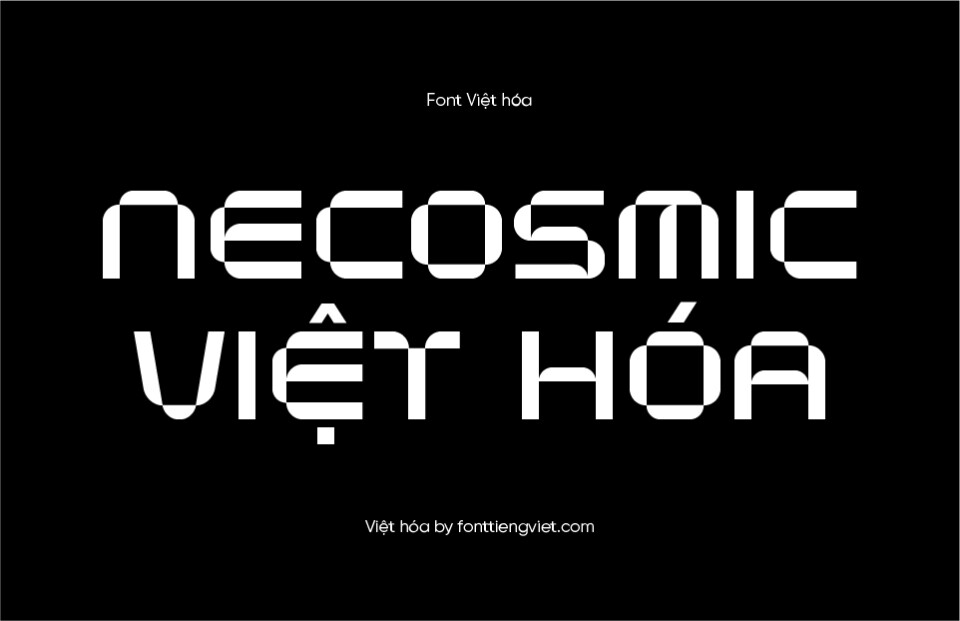
Font Việt hóa 1FTV Necosmic
Tải Font Việt hóa 1FTV Necosmic – Nét Chữ Hiện Đại Cho Thiết Kế Sáng Tạo
Giới thiệu về Font Việt hóa 1FTV Necosmic
Trong thế giới đồ họa hiện nay, việc lựa chọn một Font Miễn Phí chất lượng đóng vai trò then chốt giúp sản phẩm trở nên thu hút. Font Việt hóa 1FTV Necosmic là một trong những bộ font mang phong cách hiện đại, được thiết kế với các đường nét mạnh mẽ nhưng không kém phần thanh thoát. Bộ font này không chỉ giúp các bạn học sinh dễ dàng làm bài thuyết trình mà còn hỗ trợ đắc lực cho giáo viên trong việc soạn thảo giáo án điện tử sinh động hơn. Necosmic mang đến một hơi thở mới lạ, giúp các văn bản tiếng Việt thoát khỏi sự đơn điệu thường thấy.
Ưu điểm nổi bật của Font Việt hóa 1FTV Necosmic
Thiết kế tối giản và tinh tế
Đặc điểm lớn nhất của Font Việt hóa 1FTV Necosmic chính là sự cân bằng hoàn hảo giữa tính thẩm mỹ và khả năng đọc hiểu. Các ký tự được chăm chút tỉ mỉ, giúp hiển thị rõ nét trên cả màn hình máy tính lẫn bản in. Điều này cực kỳ quan trọng đối với các bạn trẻ đang tìm kiếm sự phá cách cho các dự án cá nhân hoặc các câu lạc bộ tại trường học.
Khả năng tương thích và Việt hóa hoàn chỉnh
Khác với các bộ font gốc thường gặp lỗi dấu tiếng Việt khi gõ, phiên bản này đã được Việt hóa 100%. Mọi dấu thanh, dấu mũ đều được tinh chỉnh vị trí chuẩn xác, đảm bảo không bị lỗi “ô vuông” khó chịu. Bạn có thể sử dụng font này trên nhiều phần mềm khác nhau như Canva, Photoshop hay Microsoft Word một cách mượt mà.
Kết luận về bộ font chất lượng